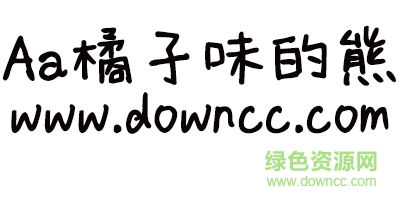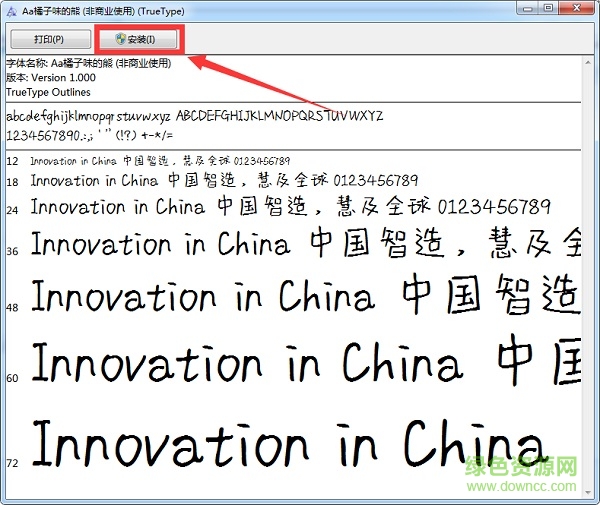
橘子味的熊字體ttf是一個(gè)免費(fèi)版的平面設(shè)計(jì)字體。這款藝術(shù)字體可以在多個(gè)行業(yè)領(lǐng)域使用,字體外觀生動(dòng)活潑,喜歡的用戶快來綠色資源網(wǎng)下載吧。
Aa橘子味的熊字體筆畫設(shè)計(jì)行云流水,字形簡約,曲線優(yōu)美,能夠適用于產(chǎn)品包裝、廣告宣傳、出版印刷、商標(biāo)用字、商業(yè)網(wǎng)站、影視影像視頻、書籍出版印刷等。有需要的用戶歡迎來綠色資源網(wǎng)下載使用。